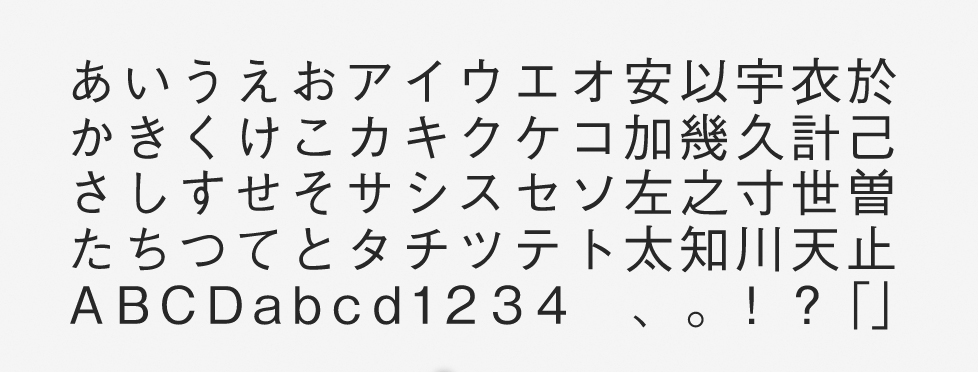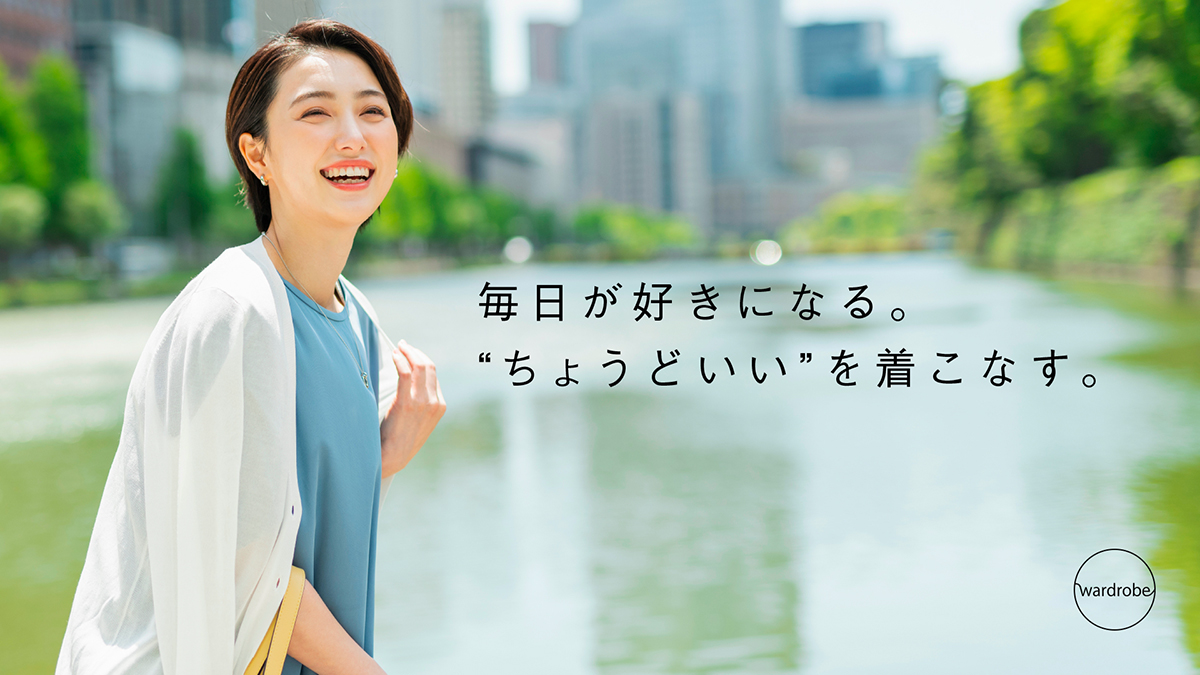
「中ゴシックBBB」について
中ゴシックBBBは、日本語DTPの歴史を語るうえでは外せない有名なフォントです。さまざまなシーンで基本書体として活用され、長きにわたって愛され続けてきました。字面が小さめであるため可読性が高く、特に「読ませる」用途に適しています。キャプションから本文などの小さな文字まで、しっかりと読ませたい場合に役立つフォントです。
「中ゴシックBBB」の特徴
中ゴシックBBBは、オーソドックスでありながら、やや有機的なクセのあるエレメントも備えています。そのため、シンプルながらも “味” のある表現が可能です。
適度な太さで、明朝体と同じレイアウトに配置しても違和感を与えないことは、使いやすさのポイントの1つ。さらに、「本文には中ゴシックBBB」「キャプションと言えばこの書体」といったイメージが強いことは確かですが、あえてタイトルなどに使用しても面白い効果を発揮します。
中ゴシックBBBは「中性的」な印象もあり、タイトル、見出し、本文、キャプションとあらゆる場所で使いやすいフォントです。見出しで使う場合には、文字どうしの間隔を広くすると、このフォントの特徴である「ヌケ感」を表現できます。普遍的な魅力があって「一生飽きない」フォントです。